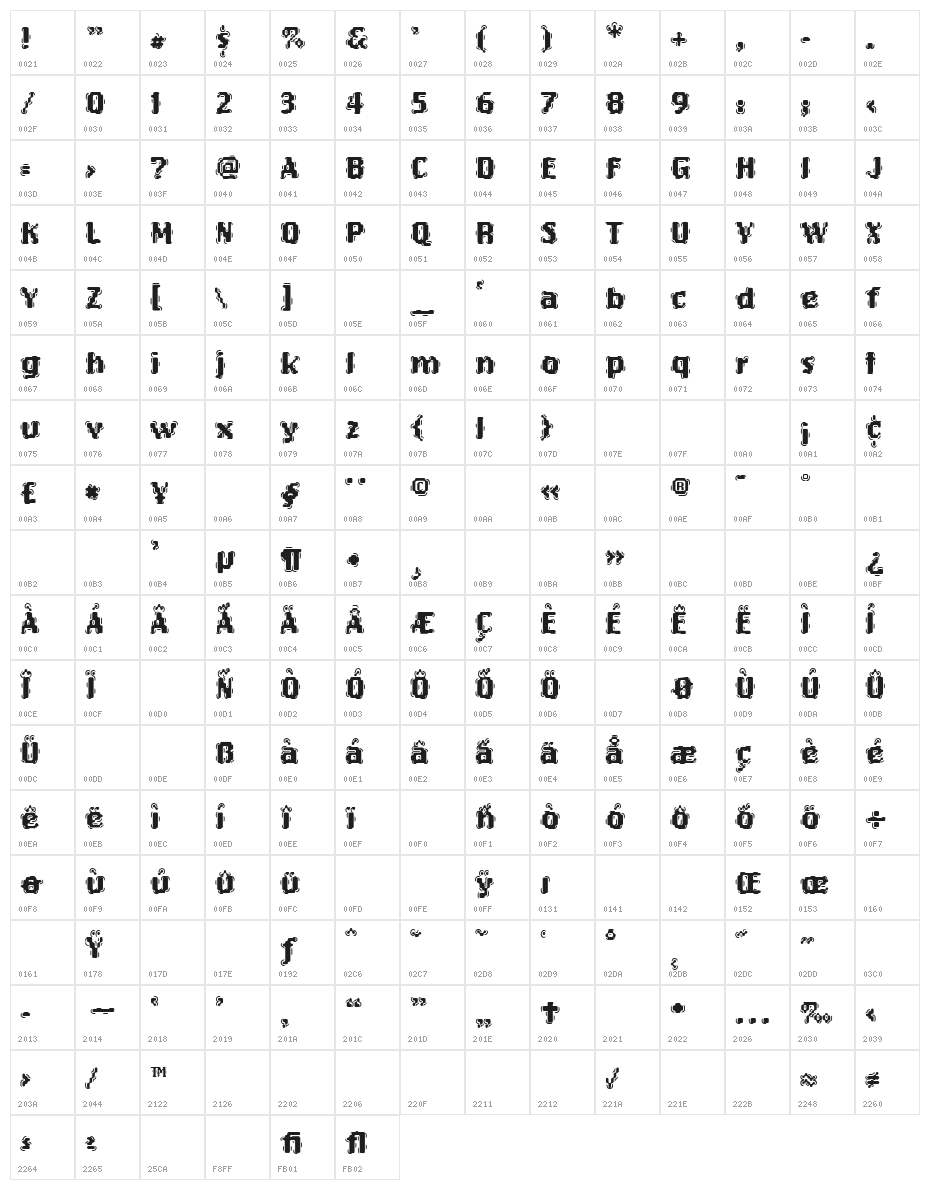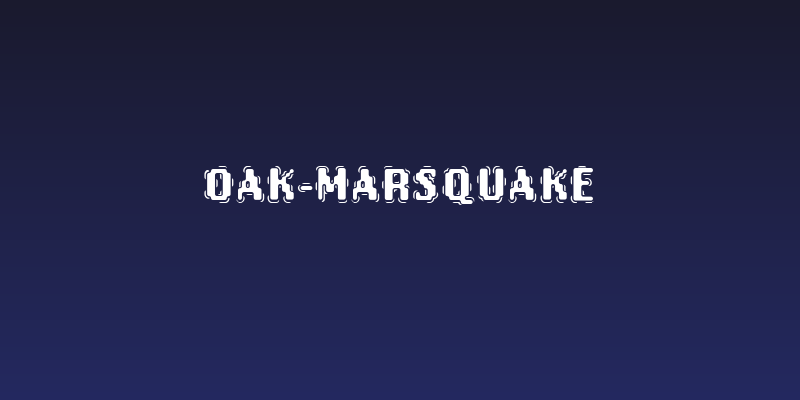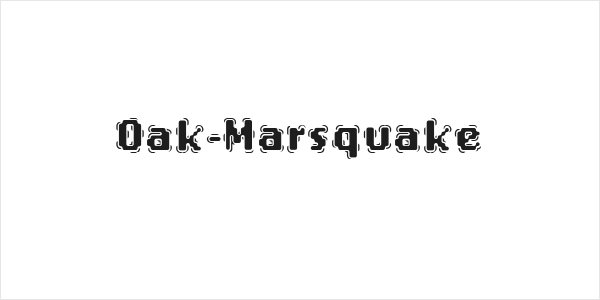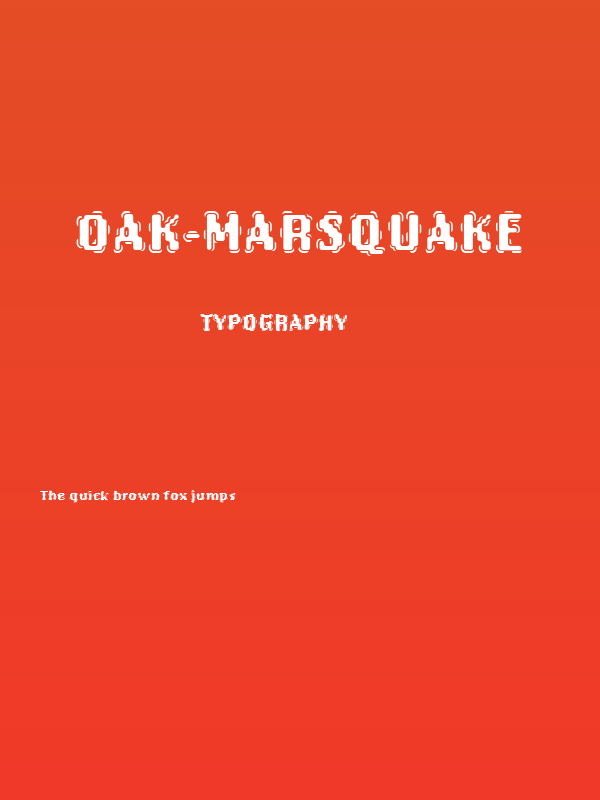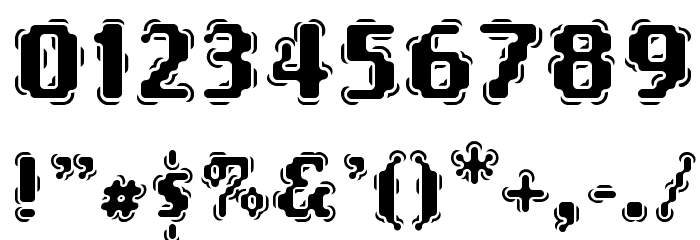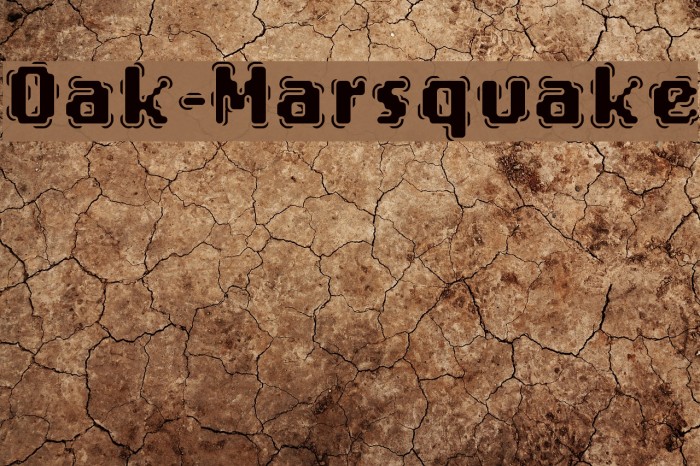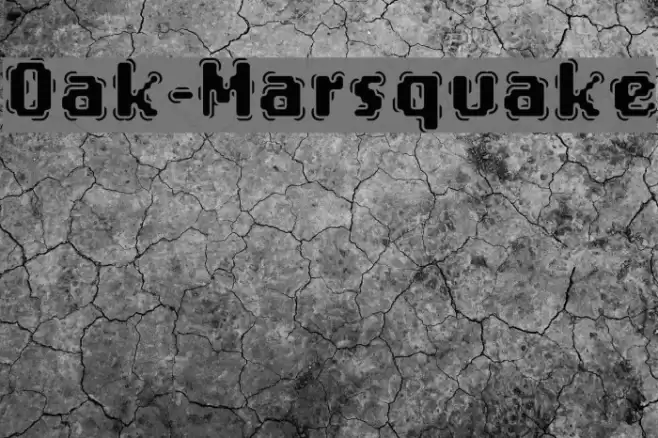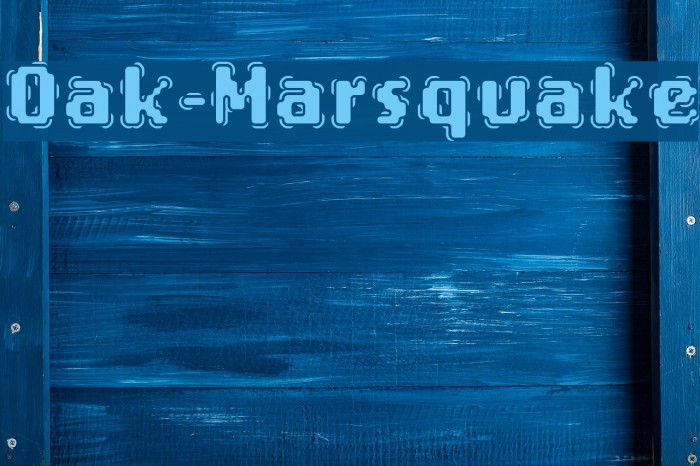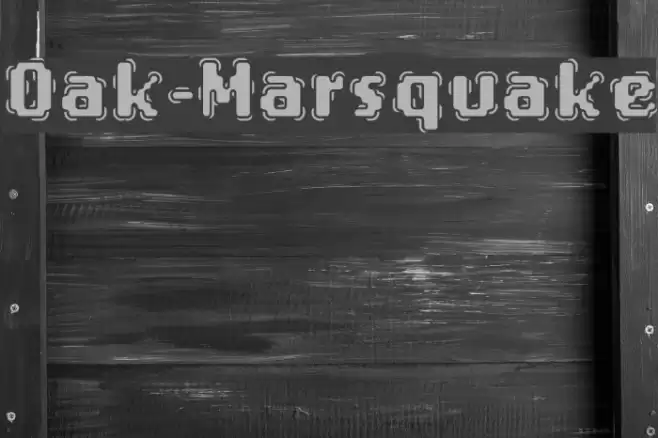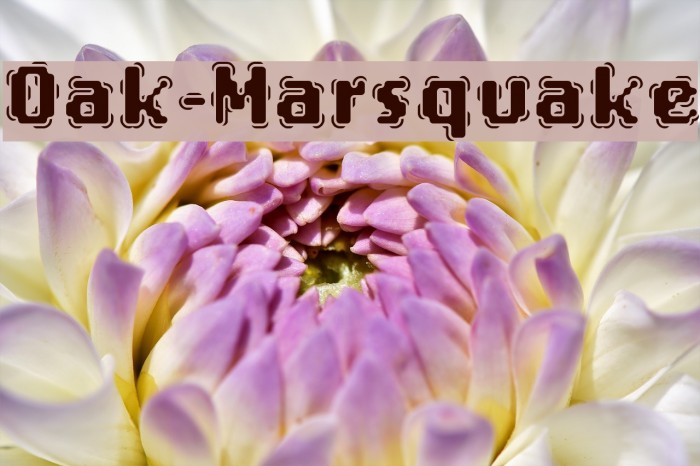
Oak-Marsquake Font
| Общий стиль | Modern, Vintage |
| Рекомендуемые проекты | Ideal for posters, logos, headlines, and any project requiring a standout, artistic typeface. |